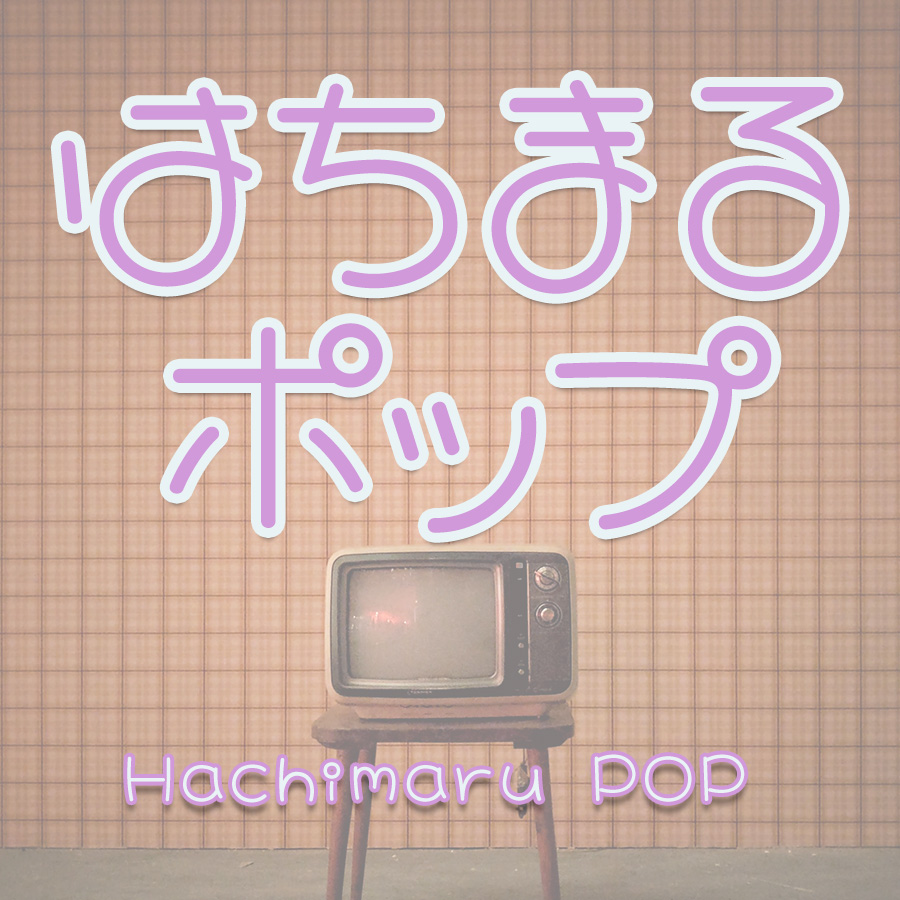
オタ活・推し活がはかどる「ポップ&手書き風」フォントセット
『かに沢のりお』は女性らしさと愛らしさを特徴とした手描き風フォントです。パステル系の可愛らしいデザインだけでなく、親しみやすくポップな印象もあり、さらにかっこいいデザインにも対応。
かに沢のりおのフォントの特徴
手書き感のあるアナログデザイン
「かに沢のりお」の書体たちの最大の特徴は、有機的でアナログ感の強いデザイン。いずれの書体も、優しさ、ぬくもり、女性らしいといった印象を持っており、タイトルやロゴデザインに活用できます。
オリジナルの装飾
一部のフォントでは、「点」などのエレメントを丸や星、ハートで装飾。女性らしさ、かわいさをより強調しています。
おすすめの使いかた
女性向けのブランドや商品プロモーションに
使用フォント:はちまるポップ・ちびすけふぉんと
イベントのポスターに
使用フォント:あめちゃんポップまる・ちびすけふぉんと
推しのネームボード・応援うちわに
使用フォント:ましゅまろポップはーと・じゃんぴょんまる
収録書体一覧
ましゅまろポップ ハート
かにさわのりお ましゅまろポップ ハート
マシュマロのようにぽってり太め、ぷにぷにと丸っこいフォントです。ハートがあちこちにまぎれています。
あめちゃんポップまる
まるをあちこちに散りばめた、ぽってりかわいいポップな太めのフォントです。
じゃんぴょんまる
かにさわのりお じゃんぴょんまる
丸を散りばめた手作りのポップ体です。
ちびすけふぉんと
かにさわのりお ちびすけふぉんと
ちびちびした丸っこいかわいいフォントです。
はちまるポップ
かにさわのりお はちまるポップ
1970から80年代に流行した、丸文字をイメージしたファンシーで丸っこいフォントです。